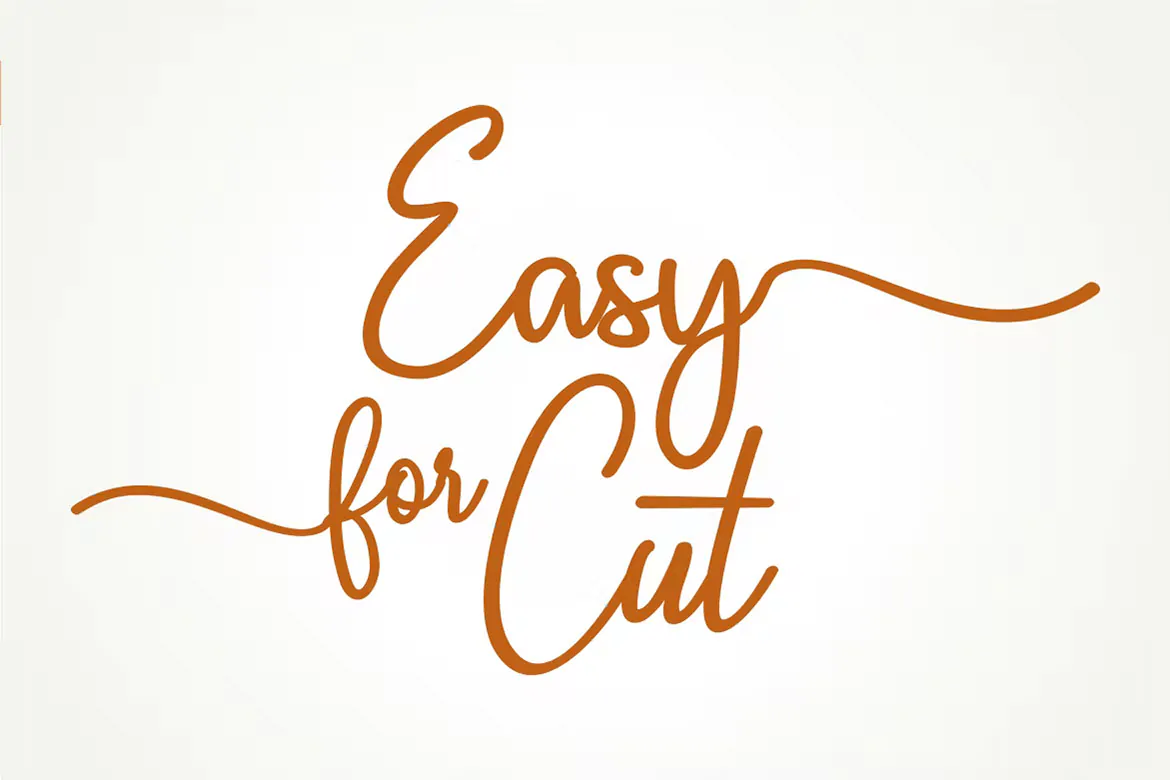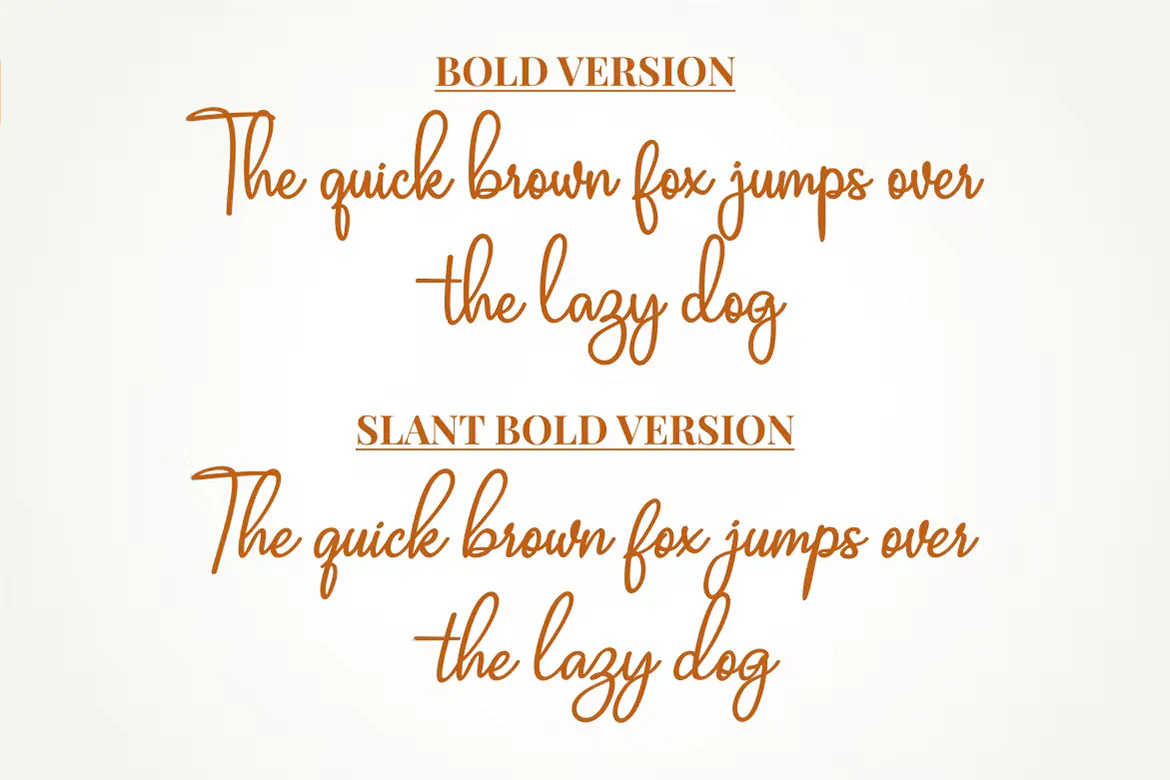
فونت سرهم کارت عروسی Darrel Allura
فونت سرهم کارت عروسی
فونت سرهم کارت عروسی Darrel Allura یک اسکریپت فونت فوق العاده زیبا است که مناسب برای استفاده در طراحی انواع کارت تبریک، کارت عروسی، پوستر، بنر، بسته بندی محصولات و … میباشد.